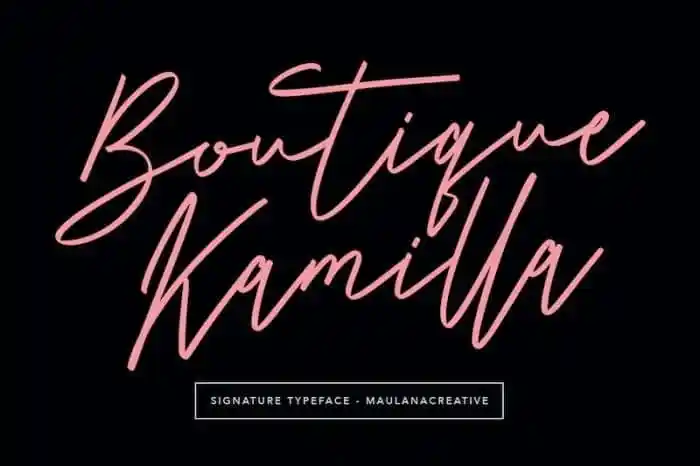
Boutique Kamilla Handwritten Font – Download Grátis
Boutique Kamilla Handwritten Font é uma elegante escolha para designers que desejam adicionar um toque autêntico a seus projetos digitais. Criação de Maulana Creative, essa fonte tem um visual de antiguidade e linhas sólidas com caracteres floridos. Suas características fluente e antiquadas permitem incorporar este estilo elegante em uma variedade de projetos: desde assinaturas e identidade visual até capas de livros e embalagens. Ideal para aqueles que desejam dar um toque autêntico aos seus materiais de marketing, desde editoriais até roupas de marca. Uma fonte perfeita para quem busca trazer uma dose extra de sofisticação a qualquer projeto.